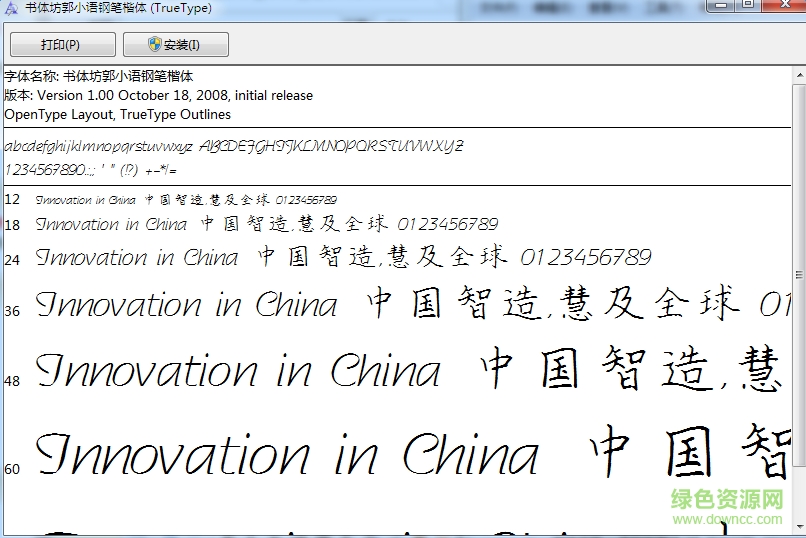
書體坊郭小語鋼筆楷體字體
書體坊郭小語鋼筆楷體是一款字形非常優(yōu)美的手寫鋼筆楷體電腦字體,結(jié)構(gòu)上字形端正、重心平穩(wěn),筆畫與筆畫、偏旁與偏旁之間比例適當(dāng),分布和諧,喜歡的朋友歡迎來綠色資源網(wǎng)下載使用!
書體坊郭小語鋼筆楷體介紹
書體坊郭小語鋼筆楷體是根據(jù)郭小語鋼筆楷體制作的一款電腦字體,外形非常美觀的楷體字,本款字體為簡體字,字形纖細(xì)、端正,整體給人秀美的視覺感受。
書體坊郭小語鋼筆楷體